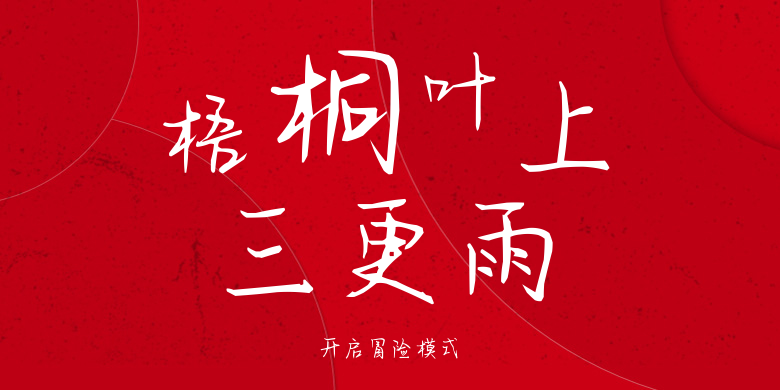
开启冒险模式
开启冒险模式,这款字体结构工整、笔画清晰,兼顾美观与易读性,适用于标题、正文、海报、包装、LOGO 等多种场景。字形优雅稳定,风格百搭耐看,适配日常排版与创意设计,让文字呈现更舒适、更具质感。开启冒险模式一笔一画,皆是细节,以均衡的比例、流畅的线条打造舒适视觉体验,字形端正大气,风格简约现代。无论是商业设计、品牌宣传还是日常排版,都能轻松驾驭,让文字更有格调与力量。开启冒险模式字体下载。